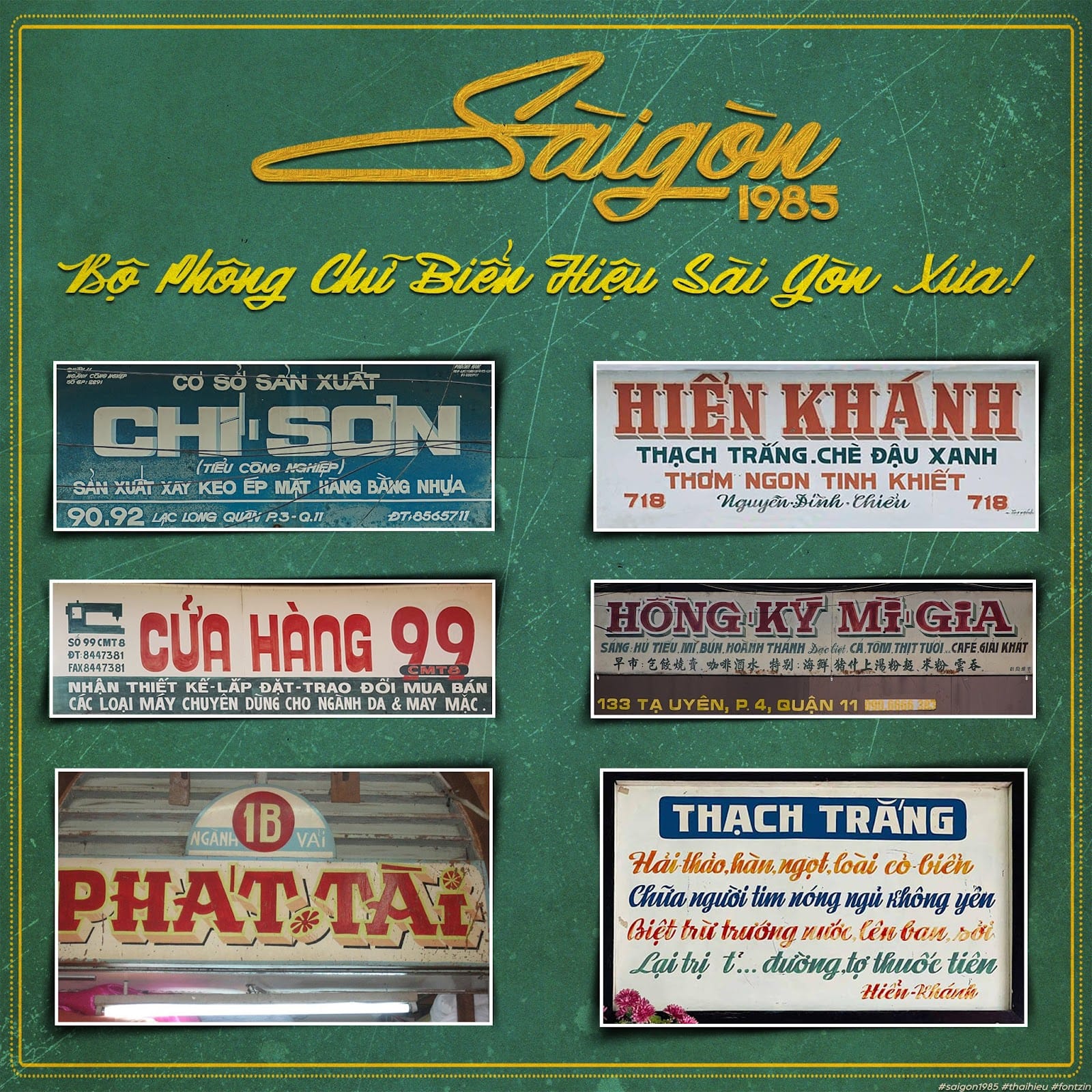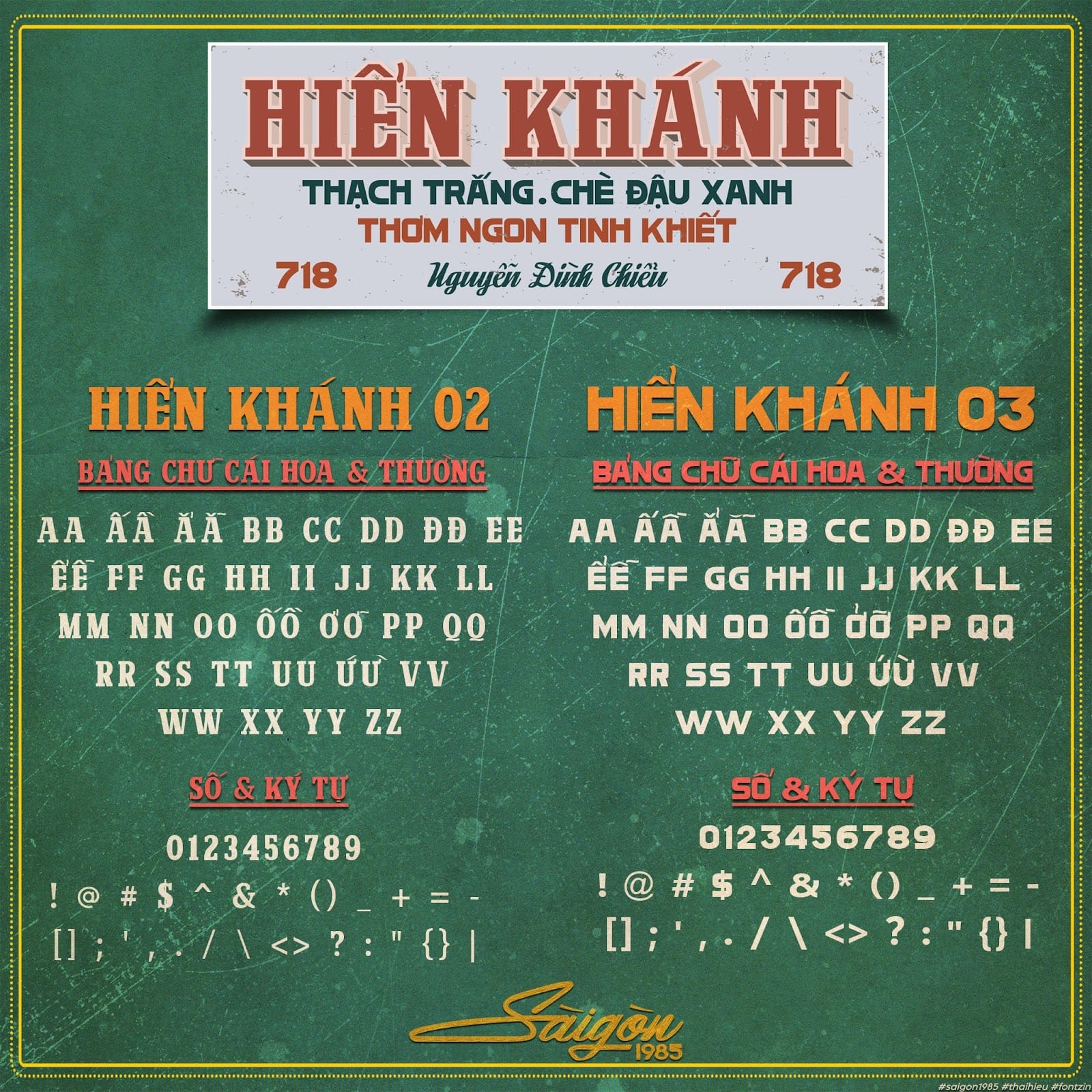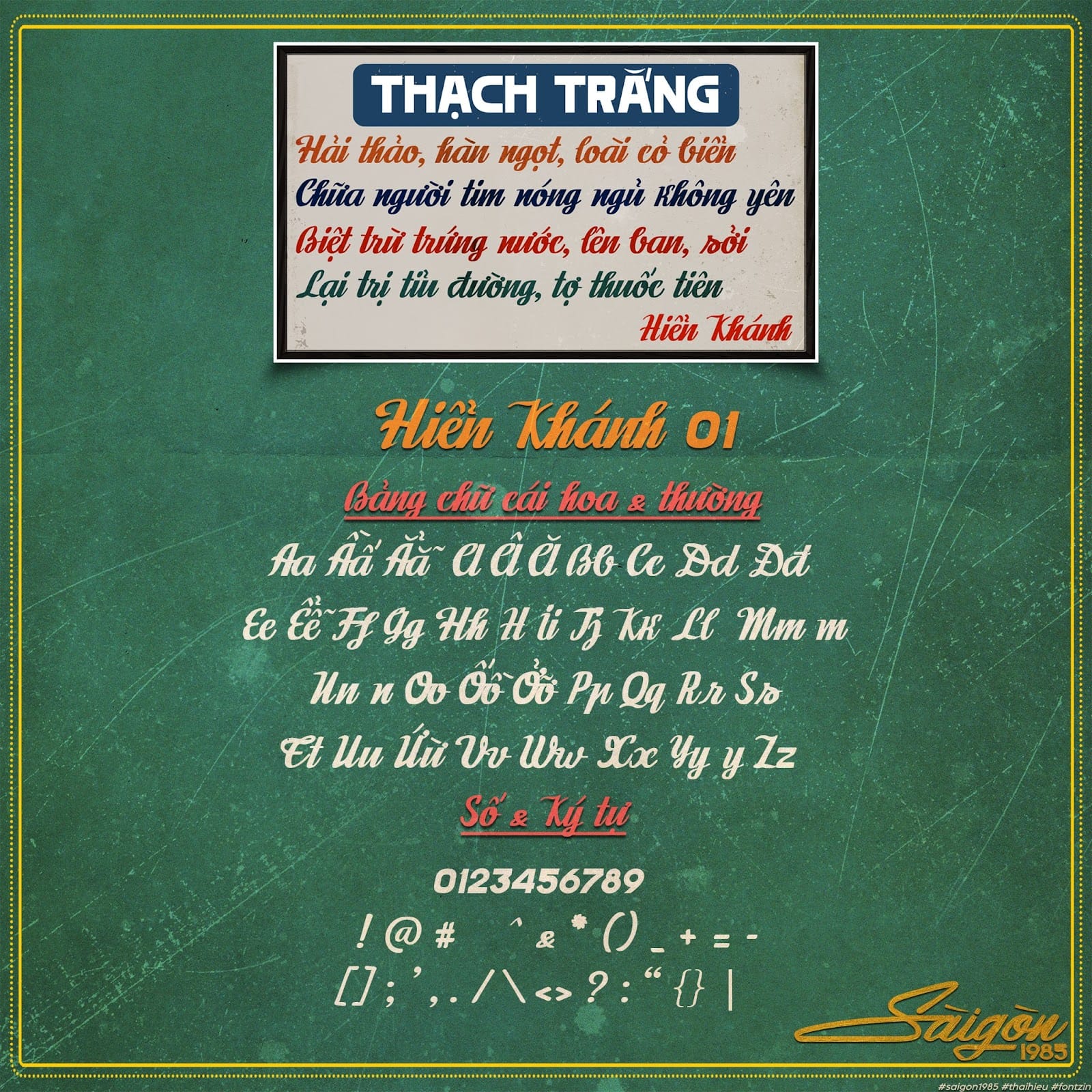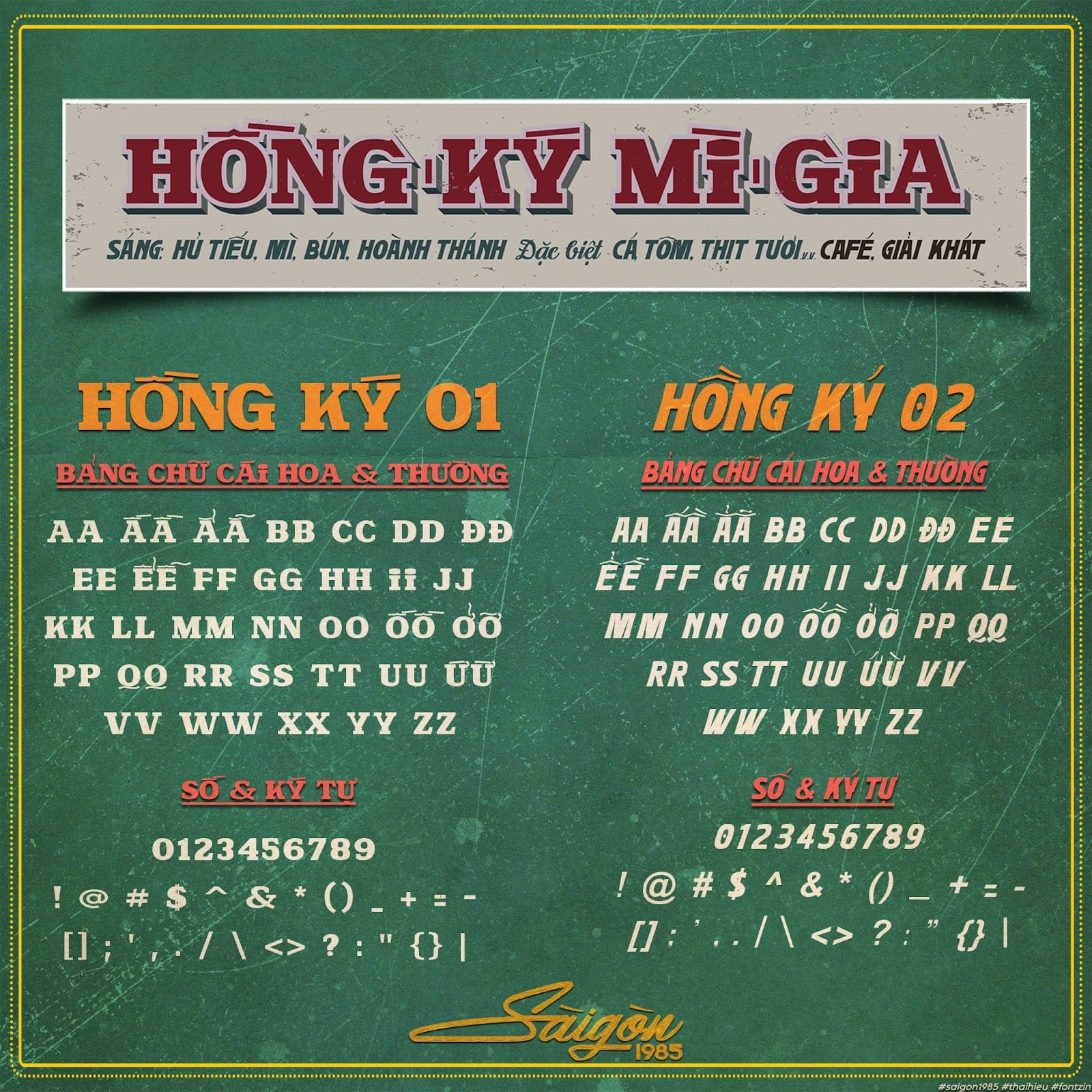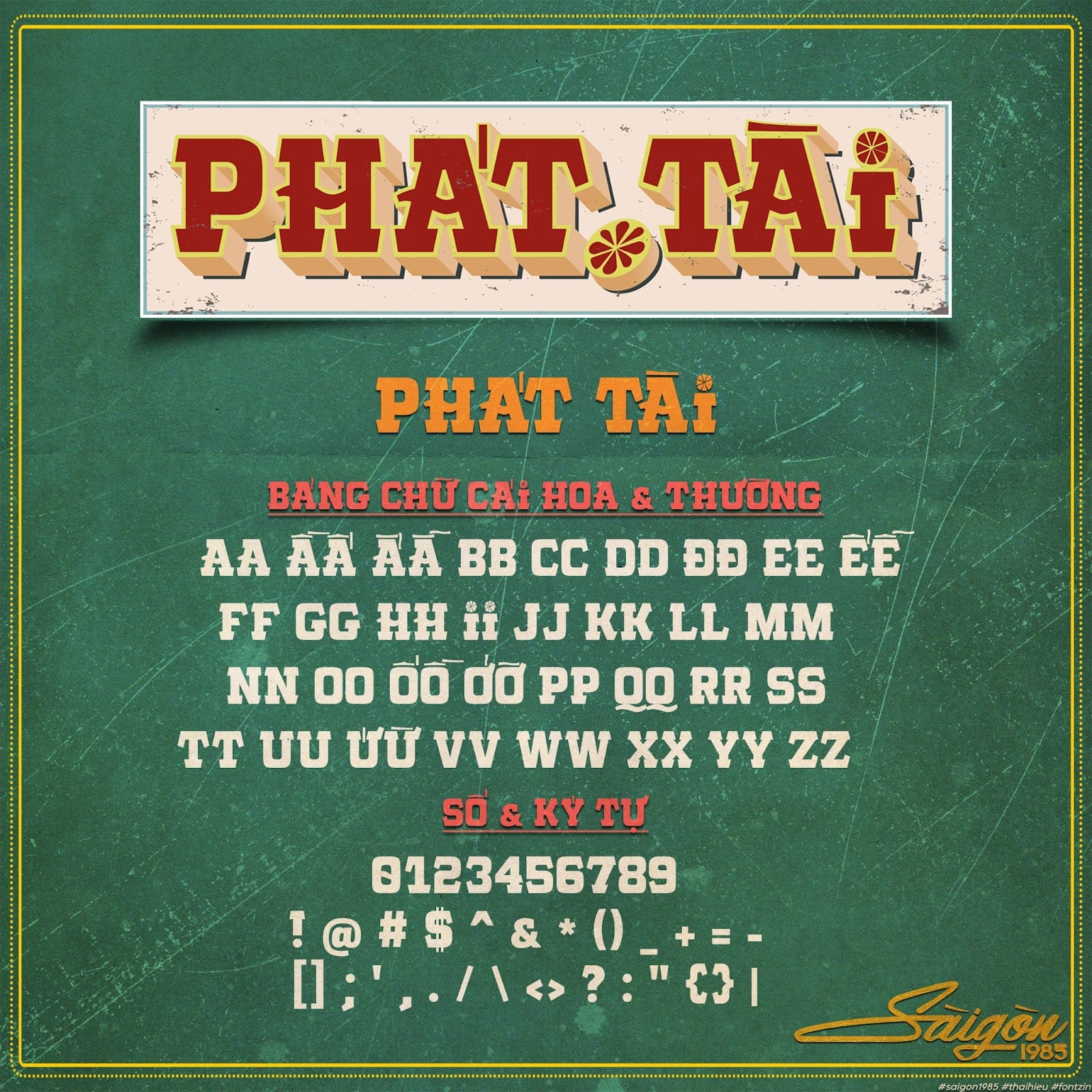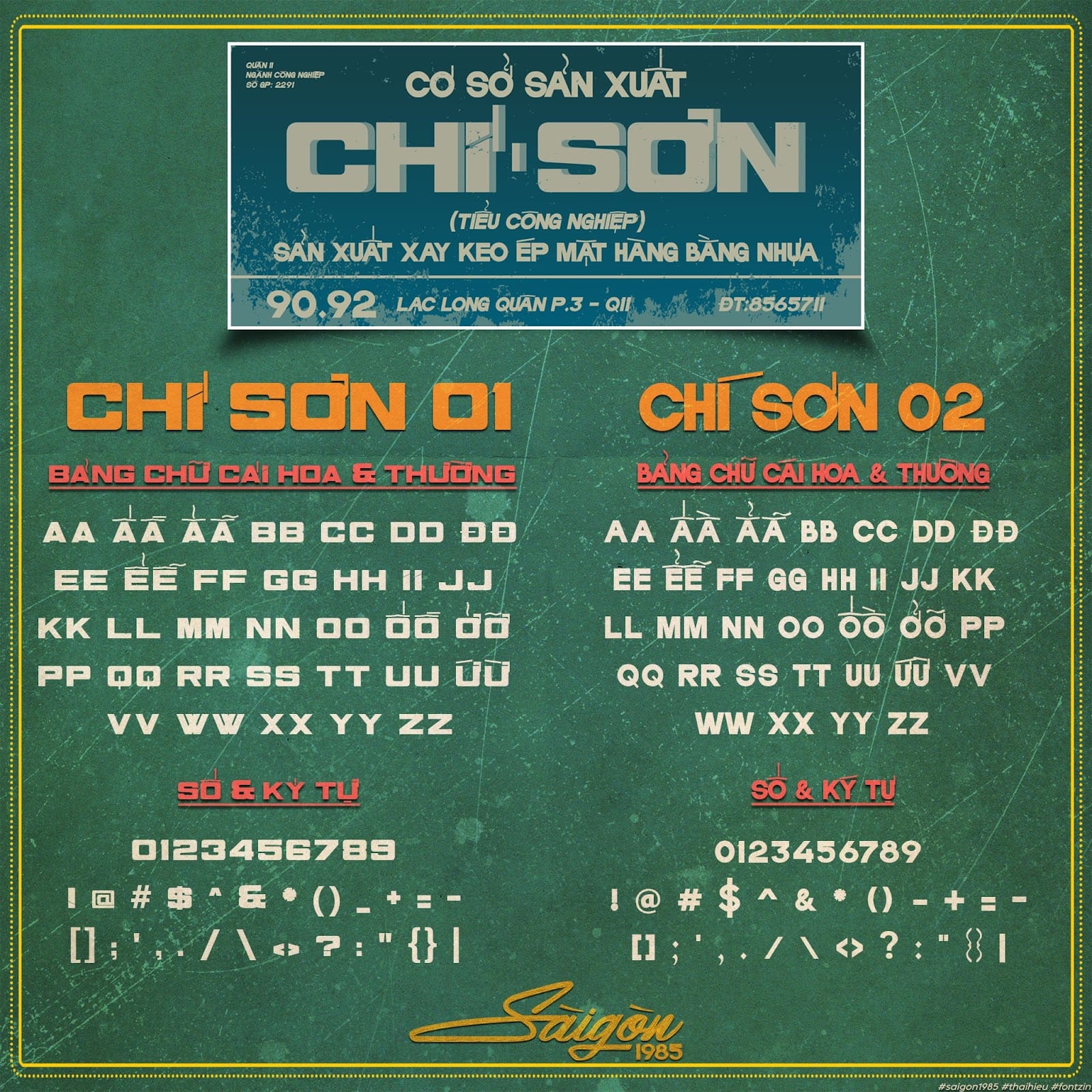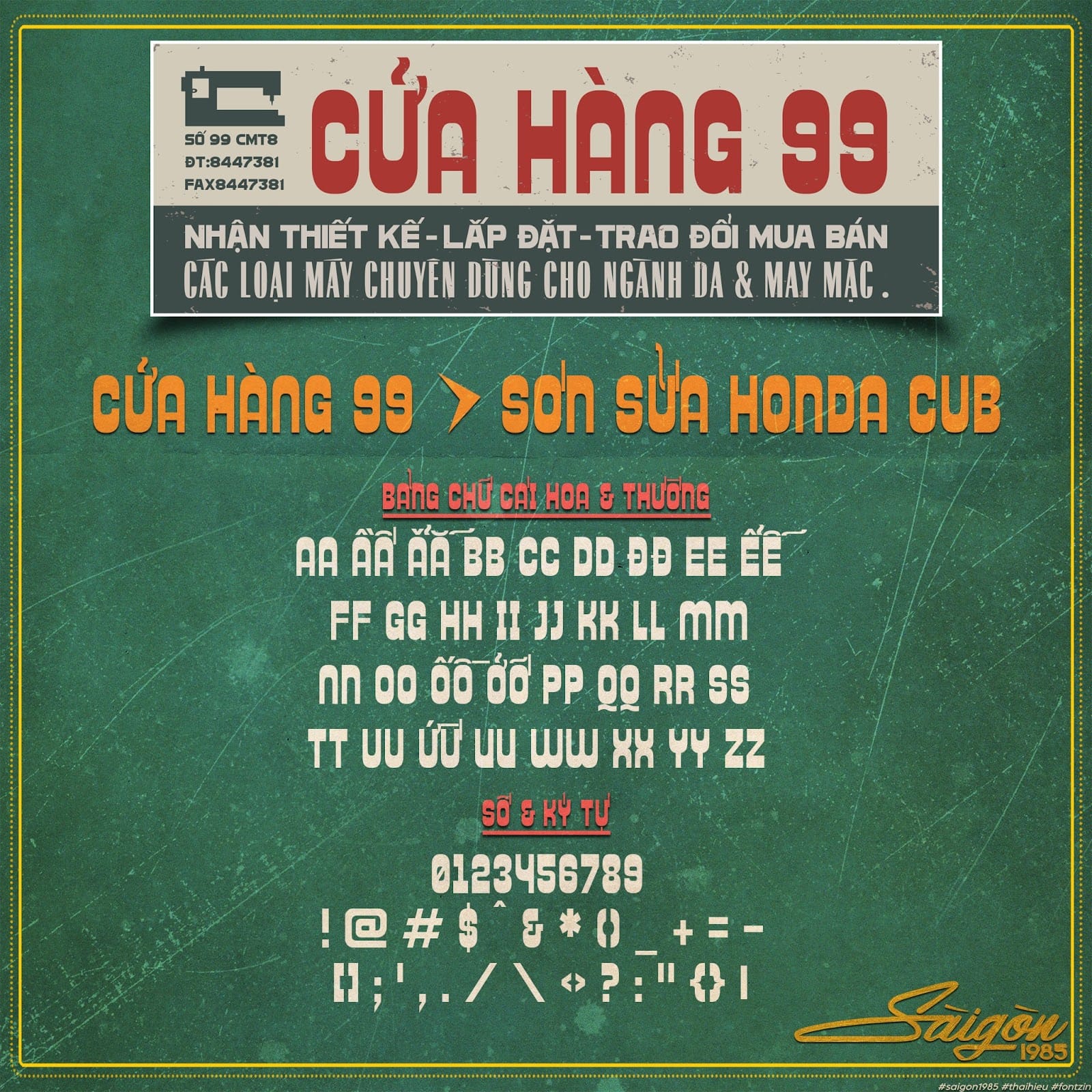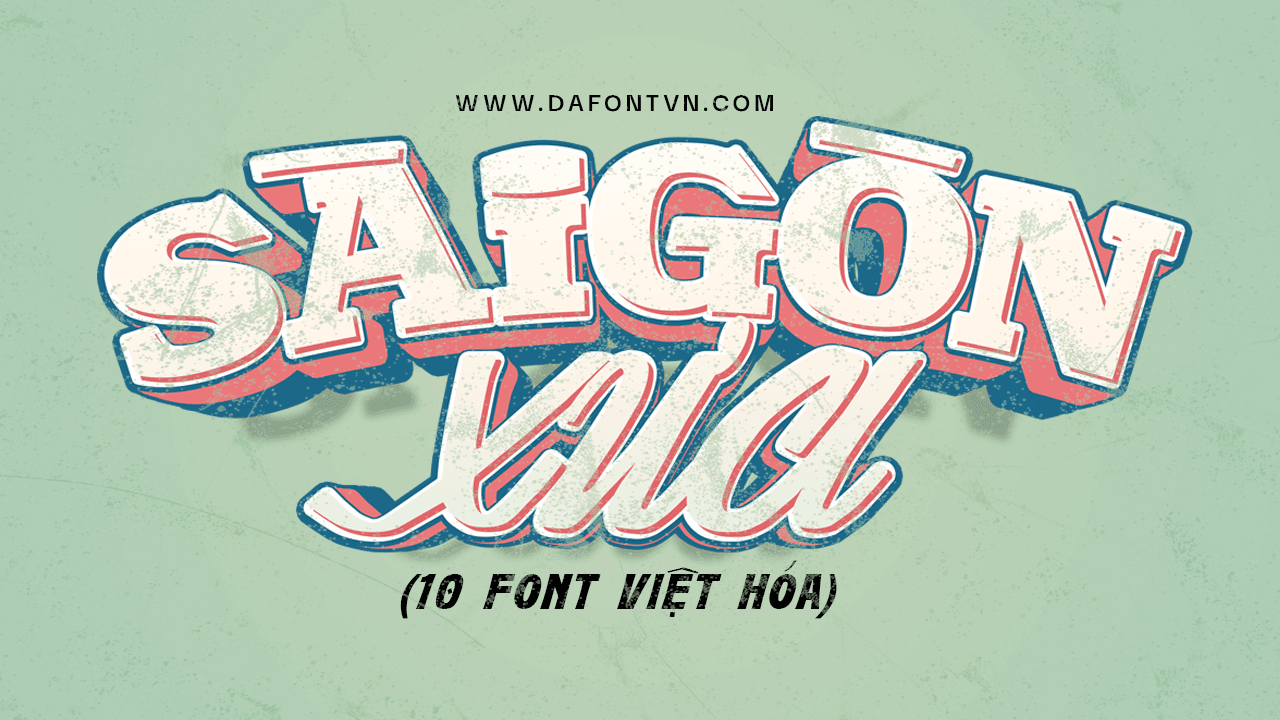
bộ font Sài Gòn Xưa (Sài Gòn 1985) mang phong cách retro lấy cảm hứng từ những biển hiệu Sài Gòn Xưa được thiết kế bởi tác giả Thái Hiếu, bộ font được chia sẻ miễn phí và có thể sử dụng cho mục đích thương mại.
Dự án gồm 10 Typeface, mỗi typeface dựa trên 1 số chữ cái trên các biển hiệu để làm thành 1 font hoàn chỉnh bao gồm các chữ cái latin A-Z, số ký tự cơ bản với kiểu dấu tiếng Việt nguyên mẫu, ngoài ra còn có một vài ký tự thay thế khác.
Bộ font Sài Gòn Xưa phù hợp cho rất nhiều dự án khác nhau nếu cần đến 1 kiểu chữ mang phong cách xưa cũ, retro, có thể sử dụng trong thiết kế biển hiệu, tạp chí, bìa sách, thiệp mời….